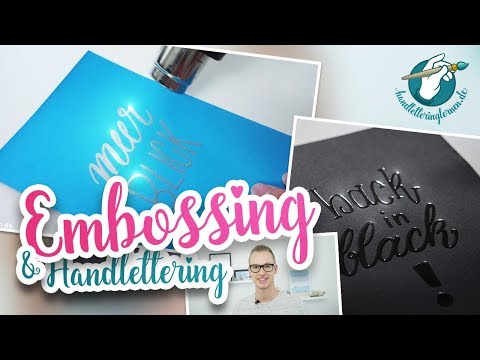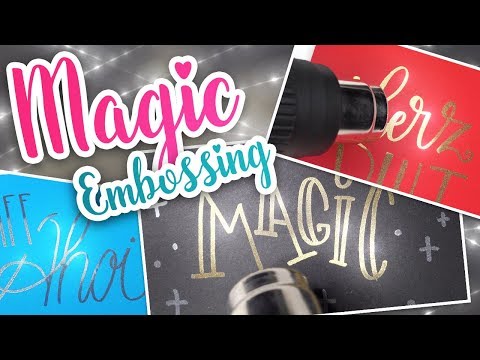
Das sogenannte Embossing erlaubt es dir, glänzende Schriften auf Papier und vor allem Pappe zu bringen.
Embossing ist das englische Wort für „Prägen“ und genau so sieht es mit der richtigen Technik auch aus. Ich möchte dir zeigen, wie du durch das Embossing besonders hochwertige, handbeschriftete Karten erstellen kannst.
In diesem Artikel erfährst du, was du alles für das Embossing brauchst und ich empfehle dir eine möglichst günstige aber dennoch gute Grundausstattung für die ersten schicken Karten.
So funktioniert’s
Beim Embossing werden feine Kunstharz-Partikel durch Hitze zum Schmelzen gebracht. Dabei verbinden sie sich zu einer leicht erhobenen, glatten Fläche, welche damit zu glänzen beginnt.
Um die Partikel in „Schriftform“ zu bringen, benötigst du einen transparenten Klebestift, auf dem die Partikel vor dem Erhitzen haften bleiben.
Wie das im Detail aussieht, erfährst du nach einem kurzen Material-Check.
Welche Materialien du bauchst
Meine kurze Einkaufsliste zeigt dir alles, was du für einen guten und günstigen Einstieg in das Embossing brauchst.
Passendes Papier
Fast jedes Papier eignet sich für das Embossing. Es sollte jedoch nicht zu dünn sein, da es sonst beim erhitzen stark wellt. Setzt du einen Embossing-Brushpen ein, sollte es außerdem nicht zu rau sein, damit du deinen Stift schonst.
Ideal eignet sich einfache Pappe (ab ca. 150-200g Papierstärke). Auf dunklen Untergründen wirken vor allem die metallischen Farben besonders schön. Folgende Pappe setze ich für meine Embossings ein:
Embossing Stifte
Damit die Partikel auf dem Papier haften, musst du deine Wörter mit einem transparenten Klebestift vorschreiben. Es gibt diese Stifte sowohl mit normaler, als auch mit Pinselspitze.
Die Pinselspitze franst auf Pappe allerdings schnell aus, sodass ich in der Regel eine normale, feste Spitze beim Embossing bevorzuge. Mit Hilfe der Faux Calligraphy sind so dennoch wunderschöne Brushlettering-Buchstaben möglich.
Embossing Pulver
Der Protagonist des Embossings ist das entsprechende Glitzer-Pulver. Es wird über die Buchstaben gestreut und später zum Schmelzen gebracht. Auch hier empfehle ich ein Starter-Set mit 4 typischen Grundfarben (Kupfer, Silber, Gold und Transparent) für die ersten Embossing-Erfahrungen.
Heißluftföhn
Etwas Technik braucht es auch. Mit einem Heißluftföhn heizt du den Partikeln ein. Ich habe mich dabei bewusst für einen Heißluftföhn entschieden, der nicht nur für den Bastelbedarf ausgelegt ist.
Er wirkt hochwertiger als die Bastel-Varianten und kann auch für andere Zwecke (zum Beispiel Sticker-Entfernung) eingesetzt werden. Meine Empfehlung stellt einen super Kompromiss aus Preis/Leistung dar und ist für jedes Hobby-Embossing mehr als ausreichend. Die Stufe 1 ist bereits heiß genug.
Achtung: Ein normaler Haarföhn reicht für das Embossing übrigens nicht aus. Er erreicht nicht die nötige Temperatur und pustet deine Partikel eher weg, als dass er sie erhitzt.
Weicher Pinsel
Ausnahmsweise wird dieser Pinsel nicht zum Schreiben, sondern zum Säubern gebraucht. Mit einem weichen Pinsel kannst du das Pulver nachträglich an die richtigen Stellen befördern und überschüssige Partikel vorsichtig entfernen. Ich habe mir dazu einfach einen Make-Up Pinsel meiner Freundin „geborgt“ … 😉
Wichtig ist, dass der Pinsel nicht zu fest ist, da du sonst auch die klebenden Partikel verschieben würdest.
Embossing in vier Schritten
1. Vorzeichnung anfertigen
Ich empfehle dir, vor dem eigentlichen Prozess, eine Vorzeichnung mit dem Bleistift zu machen. Eventuell macht es sogar Sinn zuerst auf einem anderen Papier deinen geplanten Schriftzug zu üben.
Sobald du weißt, wie du die Wörter schreiben möchtest und wie lang sie jeweils sind, kannst du dich der richtigen Pappe zuwenden.
Ich habe natürlich direkt einen Buchstaben vergessen. Zum Glück ist mir das vor dem finalen Schreiben noch aufgefallen … 🙂
2. Wort mit Klebestift lettern
Anschließend ziehst du die Wörter, die später mit Pulver bestreut werden sollen, mit einem der Embossing-Stifte nach. Für das Handlettering ist die Kombination aus dem empfohlenen Brush- und einem Bulletpen daher ideal.
Tipp: Beim Einsatz mehrerer Farben empfehle ich dir Schrittweise zu arbeiten. Schreibe erst ein Wort und führe die folgenden Schritte mit der ersten Farbe durch. Danach säuberst du dein Blatt und fängst mit dem nächsten Wort an.
3. Partikel aufbringen
Streue vorsichtig etwas Pulver über deine Buchstaben. Du musst dabei nicht mit der Menge geizen, da du das überschüssige Pulver anschließend wieder einsammelst. Wichtig ist, dass jeder Buchstabe vollständig mit Pulver bedeckt wird.
Klopfst du seitlich gegen das Papier, verteilen sich die Partikel bereits wunderbar. Letzte Korrekturen kannst du mit einem Pinsel machen. Streiche dabei ganz vorsichtig das Pulver über die letzten freien Stellen deiner Buchstaben.